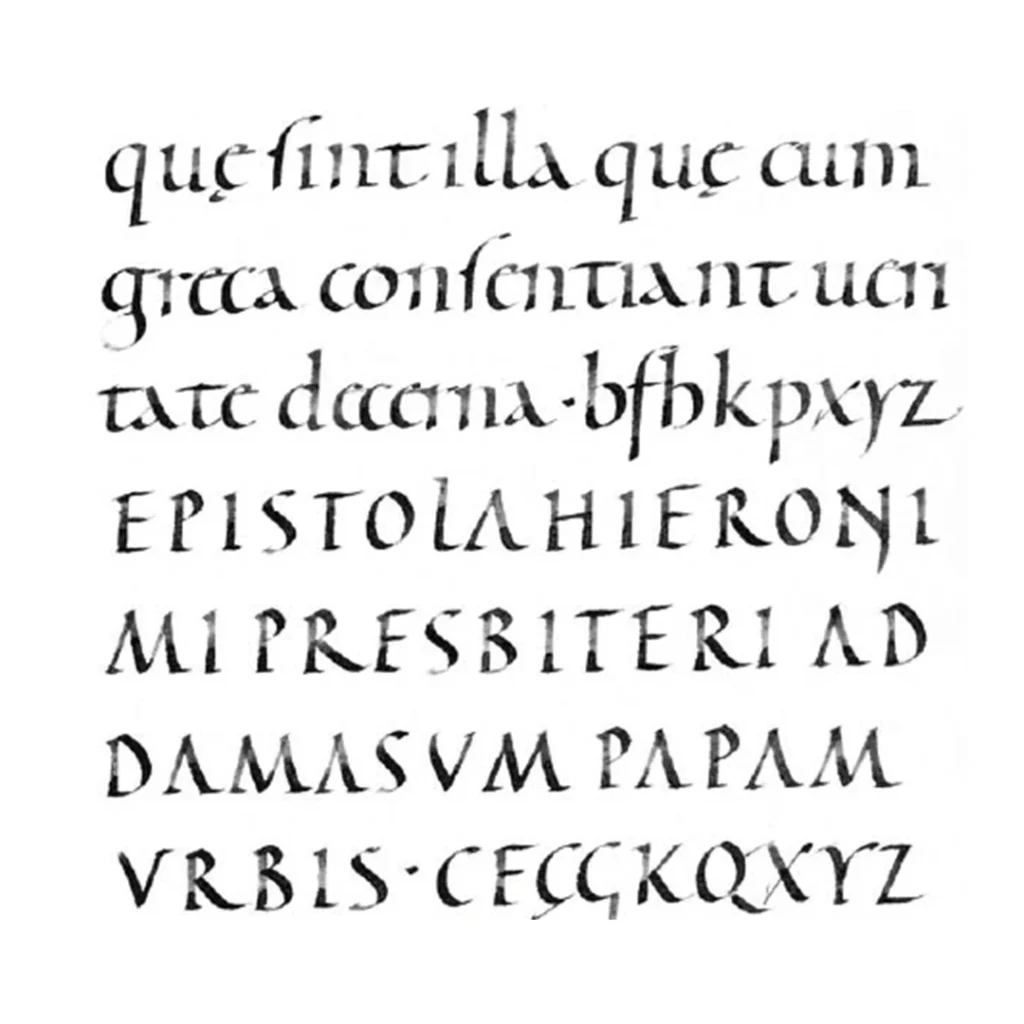
CAROLINA O CAROLINGEA
CALIGRAFÍA. Durante el siglo 8 DC, con el reinado de Carlomagno surge esta nueva escritura: la carolina o carolingia. Originalmente atribuida a Alcuino, actualmente se sabe que se desarrolló en varios puntos del imperio al mismo tiempo. El nuevo orden político y religioso universal debía ir acompañado de una nueva escritura también universal y este papel lo desempeñó la escritura carolina.
Sin duda su éxito se debió en gran medida a su alta legibilidad. Pretendía ser transmisora de cultura a nivel general y tenía como imperativo fundamental la claridad y facilidad de lectura impulsada por varios métodos, como el ductus preciso de las letras, la tendencia a separar palabras, el uso escaso de ligaduras y la restricción del empleo de abreviaturas.
La carolina es la recuperación de la antigua minúscula utilizada en los códices de los siglos IV y V con un trazado preciso y cuidado.